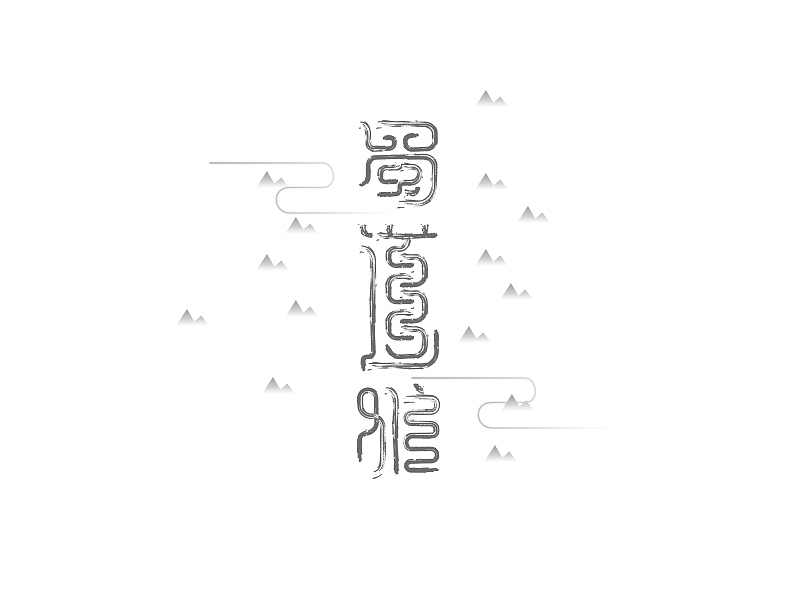
自言字语三两事·以字叙生活!
我是大猫,我为喂自己袋盐。
最近对禅产生了浓厚的兴趣,世间万物本相通,设计亦如此。
所以这期里赋予了几组字禅的味道,希望大家喜欢!
蜀道难
时光
年轮
梦境
深渊
回归
剪影
·蜀道难·
蜀道之难
难于上青天
侧身西望长咨嗟
……
·时光·
光阴似箭,流年若水
留不住的昨天
停不下的时间
记忆中的片段逐渐被风霜磨淡
守不住的记忆
守不住的时间
……
·年轮·
岁月的水滴轻轻落下
激起一圈又一圈涟漪
那是你来过的足迹
留下了永恒的印痕
承载着光阴的故事
镌刻着别样的青春
我看不到你的故事
却听得到你的沧桑
轻闭双眸
让这轮回之眼
带我回到过去的时间
……
·梦境·
一场噩梦,没有往生
佛曰:人生有八苦:生,老,病,死,爱别离,怨长久,求不得,放不下。
人生在世,浮浮沉沉,皆是南柯一梦。
梦境二字,我想把禅的味道与噩梦的感觉结合起来,当时发到群里,很多人说看了这俩字很不爽,也不好看。
我笑了笑,看了感觉浑身不舒服,那我的效果就达到了,许多人都觉得梦境就是夕阳西下、花草天堂,但事实并不是如此,我们需要惊醒,生于梦中,活于梦中,归于梦中。
……
·深渊·
佛曰“苦海无边,回头是岸”,为何我回头看到的是万丈深渊?
婆娑世界,我只能拼命前行,心之所向便是佛。
不放屠刀,不回头。
……
·回归·
一切一切由始而终
路途的长久跋涉
早已疲惫不堪的我们
是否还记得启程时的梦想
是时候回归最初的那个原点了
不要再被坎坷的路途磨灭掉
有梦,有未来。
……
·剪影·
朦胧之美
为什么我热爱剪影?
因为它是阳光之下的见证。
……